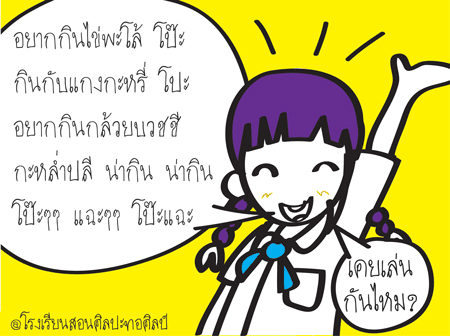
torsilp-wadkhen
ลายมือของเด็กๆ เปลี่ยนแปลงอยู่เสมอและตลอดเวลา
จวบจนกว่าเขาจะโตเข้าสู่วัยผู้ใหญ่
คงเปลี่ยนแปลงลายมือไปอีกหลายครั้ง
การทำฟอนต์ลายมือลูกของผมในครั้งนี้
เหมือนเป็นการบันทึกความทรงจำในวัยเยาว์ของเขาไว้
เป็นตัวหนังสือลายมือของเขา
ความทรงจำที่แสนมีค่านี้
ได้ถ่ายทอดลงฟอนต์นี้ได้ครบถ้วน
ความเปลี่ยนแปลงเป็นเรื่องปกติที่ต้องเป็นไป
การบันทึกความทรงจำมีหลากหลายรูปแบบและแตกต่าง
การทำฟอนต์ลายมือของลูกเก็บไว้
ถือเป็นการเก็บความทรงจำที่ดีในรูปแบบหนึ่ง
และ การบันทึกความทรงจำลงเป็นฟอนต์
ก็จะเป็นความทรงจำที่ไม่มีวันจางลงไปตามเวลาที่ผ่านไป
ระจัน
ผู้เขียนฟอนต์ torsilp-wadkhen
ด.ญ.วาดเขียน
เจ้าของลายมือ